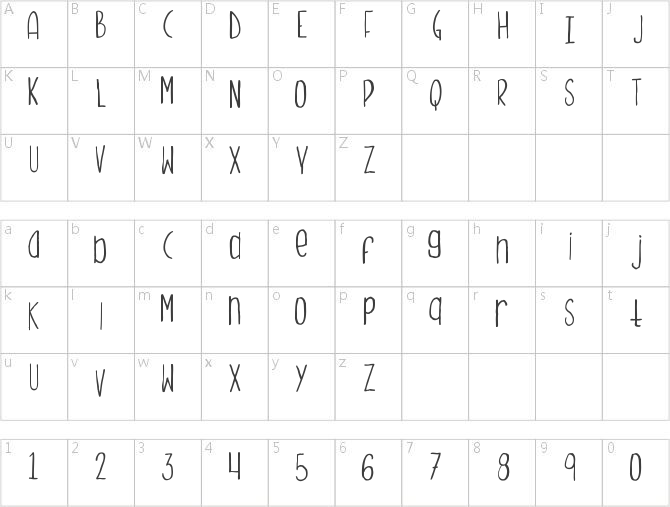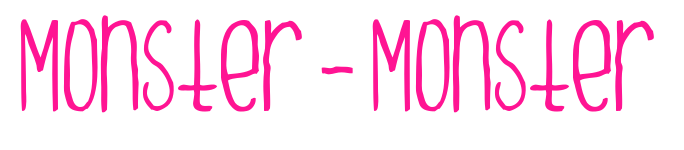
Monster-Monster 詳情頁(yè)
Monster-Monster字體字庫(kù)是一款讓人賞心悅目、百看不厭的英文字體,適合各類(lèi)廣告和產(chǎn)品包裝設(shè)計(jì)應(yīng)用,字體大小0.04MB,格式為ttf字體,上傳用戶(hù)是釜源貿(mào)易,作者/版權(quán)方為未知